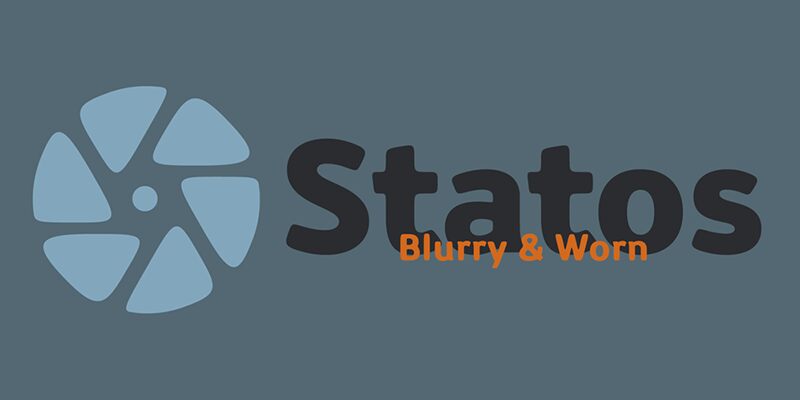
Statos Bold von deFharo ist eine kostenlose, abgerundete serifenlose Schrift mit weichem, kräftigem Rhythmus und einem freundlichen 70er-Jahre-Pop-Feeling. Die Buchstaben setzen auf große Kurven, kompakte Proportionen und stumpfe Verbindungen, die das Schriftbild lebendig und schwungvoll wirken lassen, statt geometrisch oder streng.
Das macht diese Schrift ideal für Verpackungsdesign, Café-Branding, Kinderbuchcover, lockere Plakate, App-Titel und kurze Social-Media-Grafiken, bei denen ein persönlicher Ton wichtiger ist als Formalität. Als kostenloser Font eignet sie sich am besten für kurze Überschriften, Logos und Headlines, da ihre dicken, fülligen Formen sehr schnell eine Menge Stimmung transportieren.
Statos is a worn, blurred sans-serif typeface, built on the conviction that imperfection is not a flawit's the message.
Statos questions typographic perfection. It moves away from absolute cleanliness to embrace imperfection as a visual language. And yet, it maintains exceptional legibility.
The family is structured around seven weights, seven states of controlled decayLight, Regular, Medium, Semi Bold, Bold, Extra Bold, and Blackthat maintain this eroded identity without sacrificing hierarchy or performance.
Statos includes six complete sets of numbers so that each digit tells its own story. Three sets of uppercase letters that converse with each other. Five sets of lowercase letters because versatility doesn't compromise on monotony.